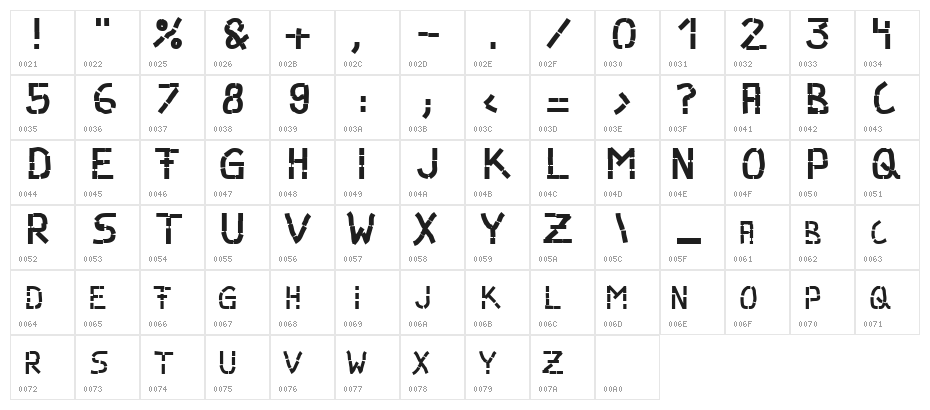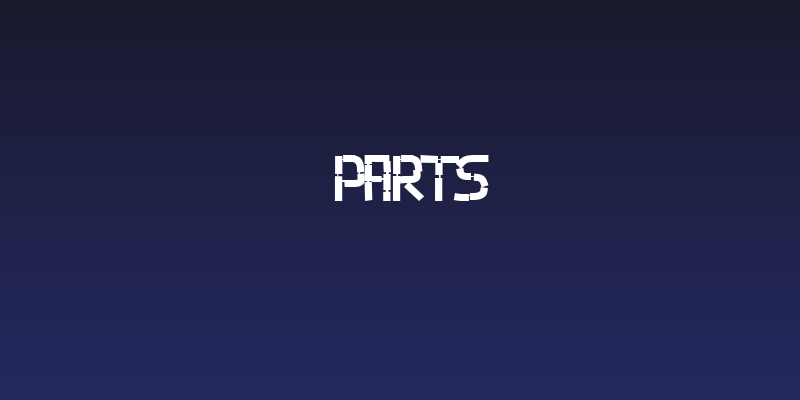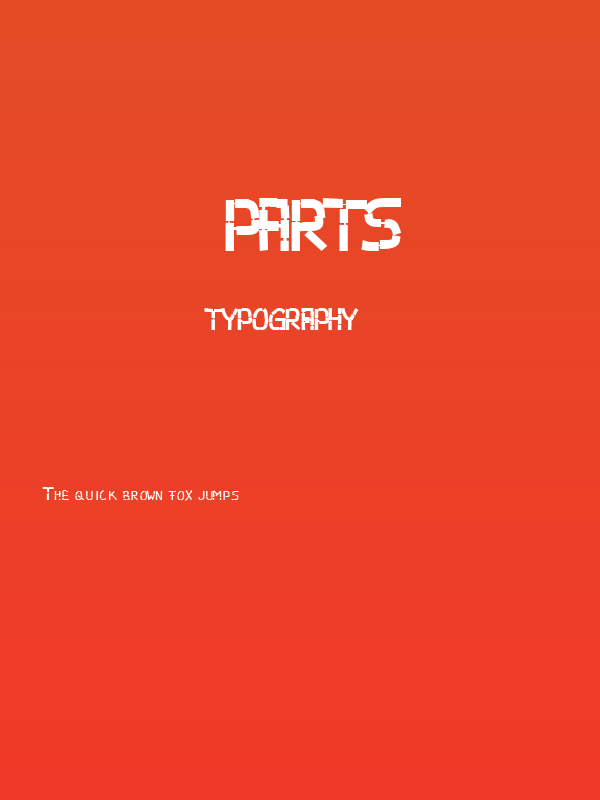
Parts Font
✎ Stencil
| Categorii | Stencil |
| Stil general | Modern, Digital |
| Proiecte propuse | Ideal for tech-themed designs, digital art, posters, and branding that requires a modern, edgy look. |